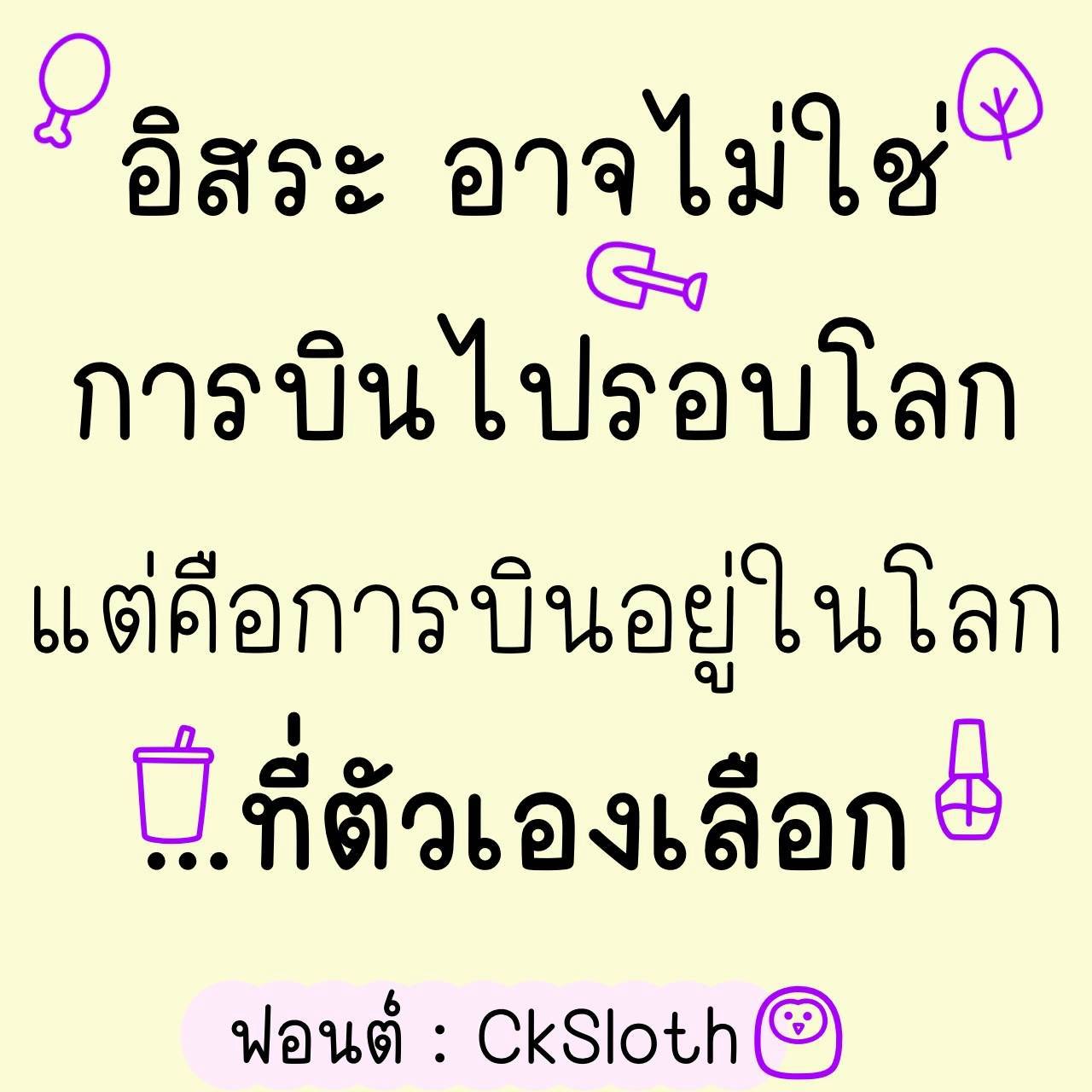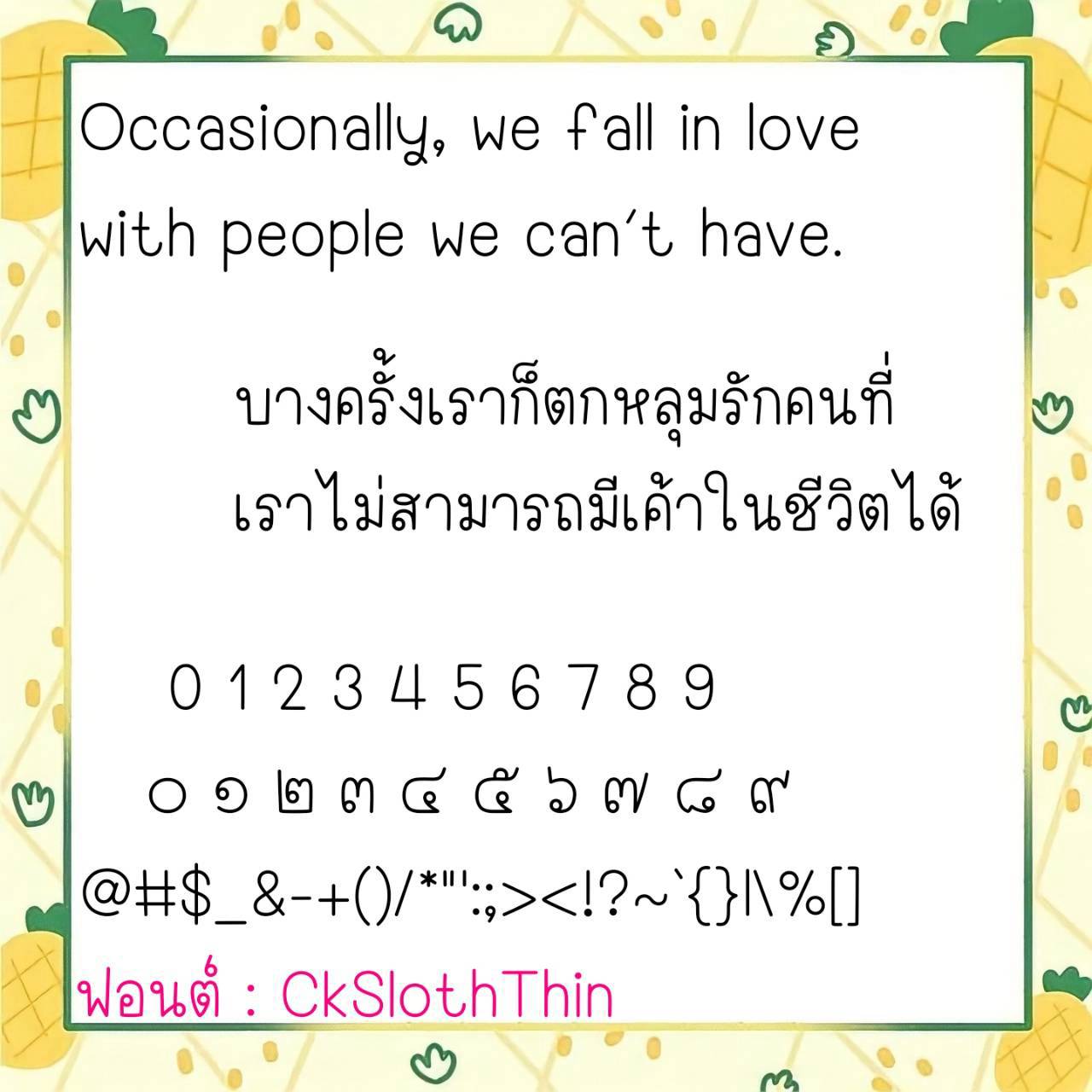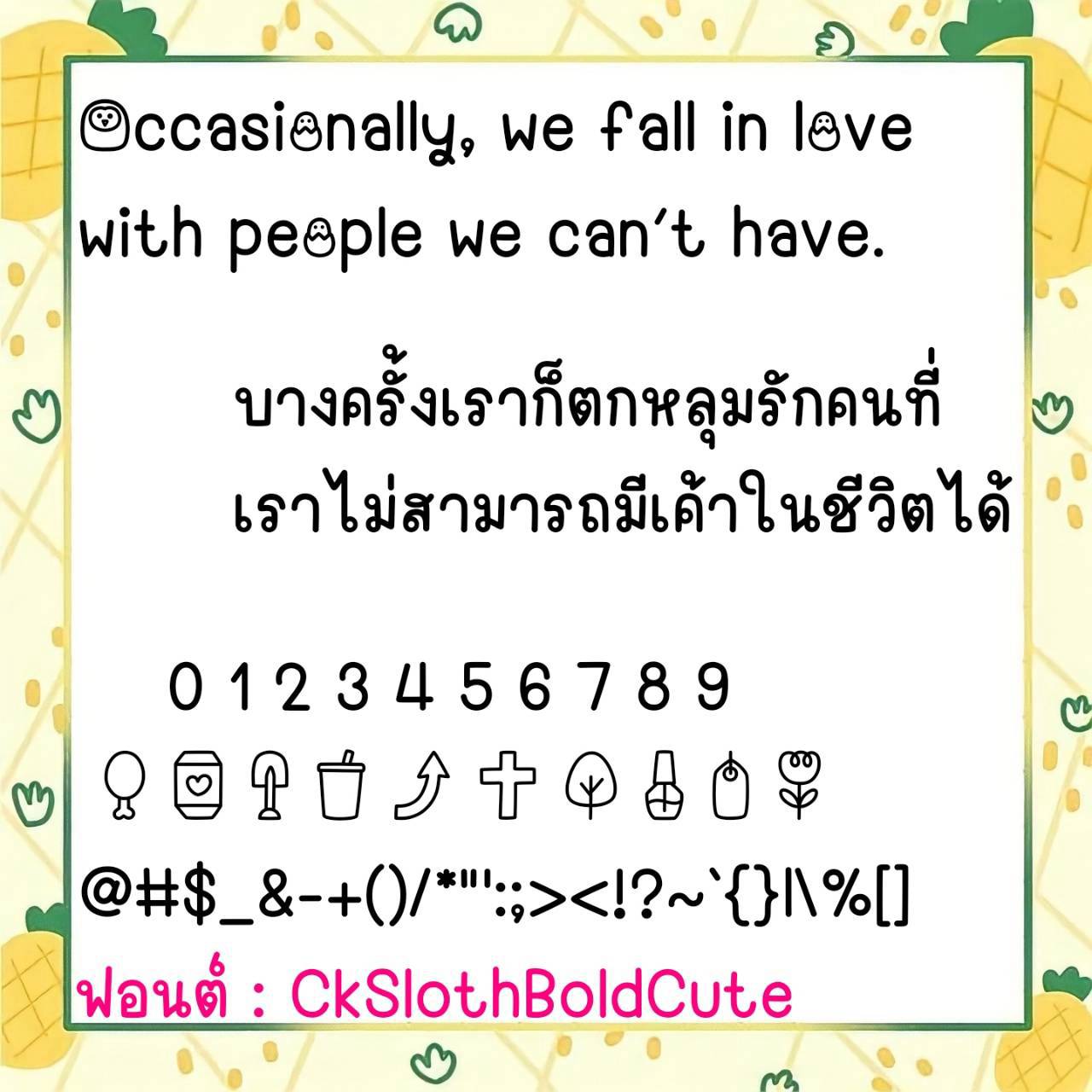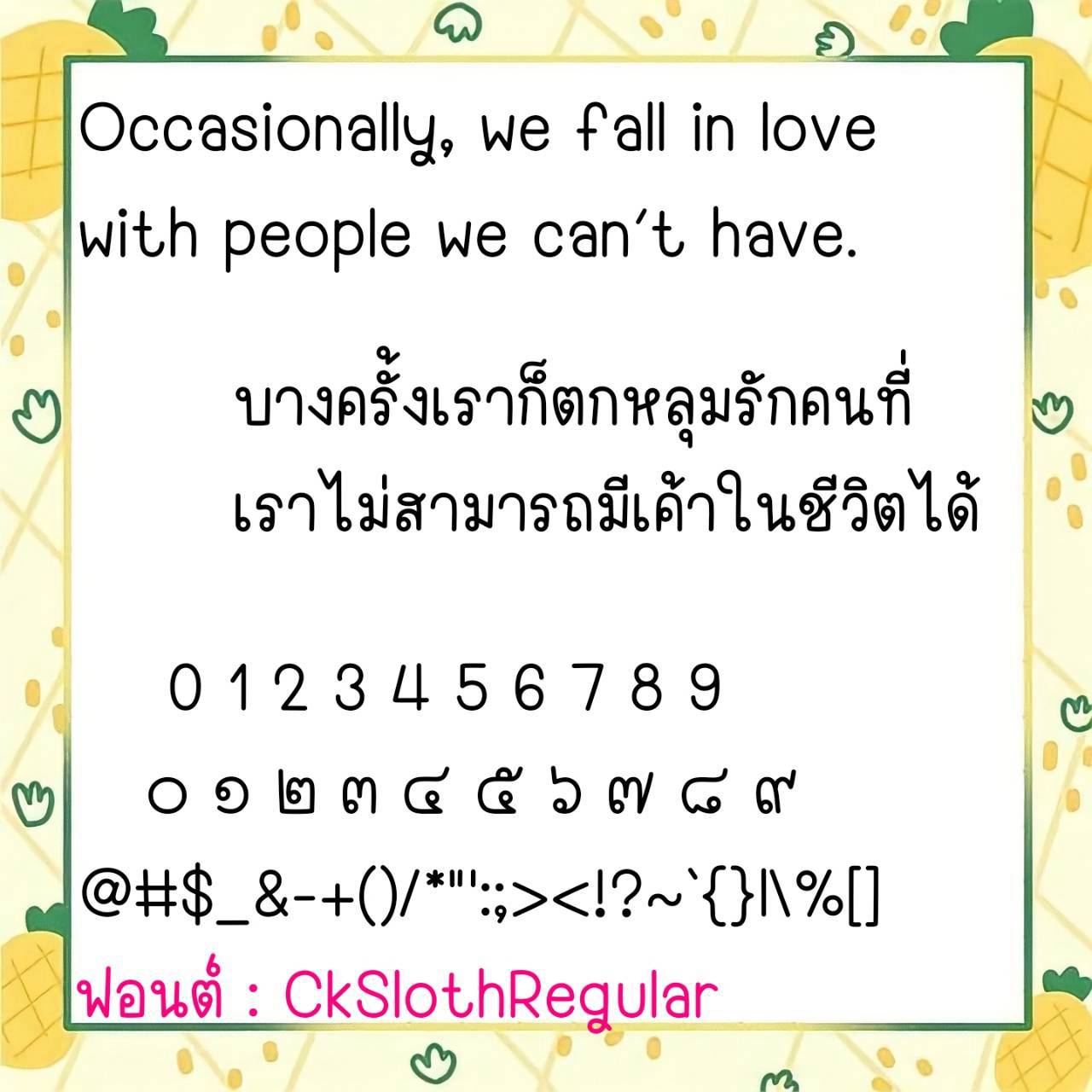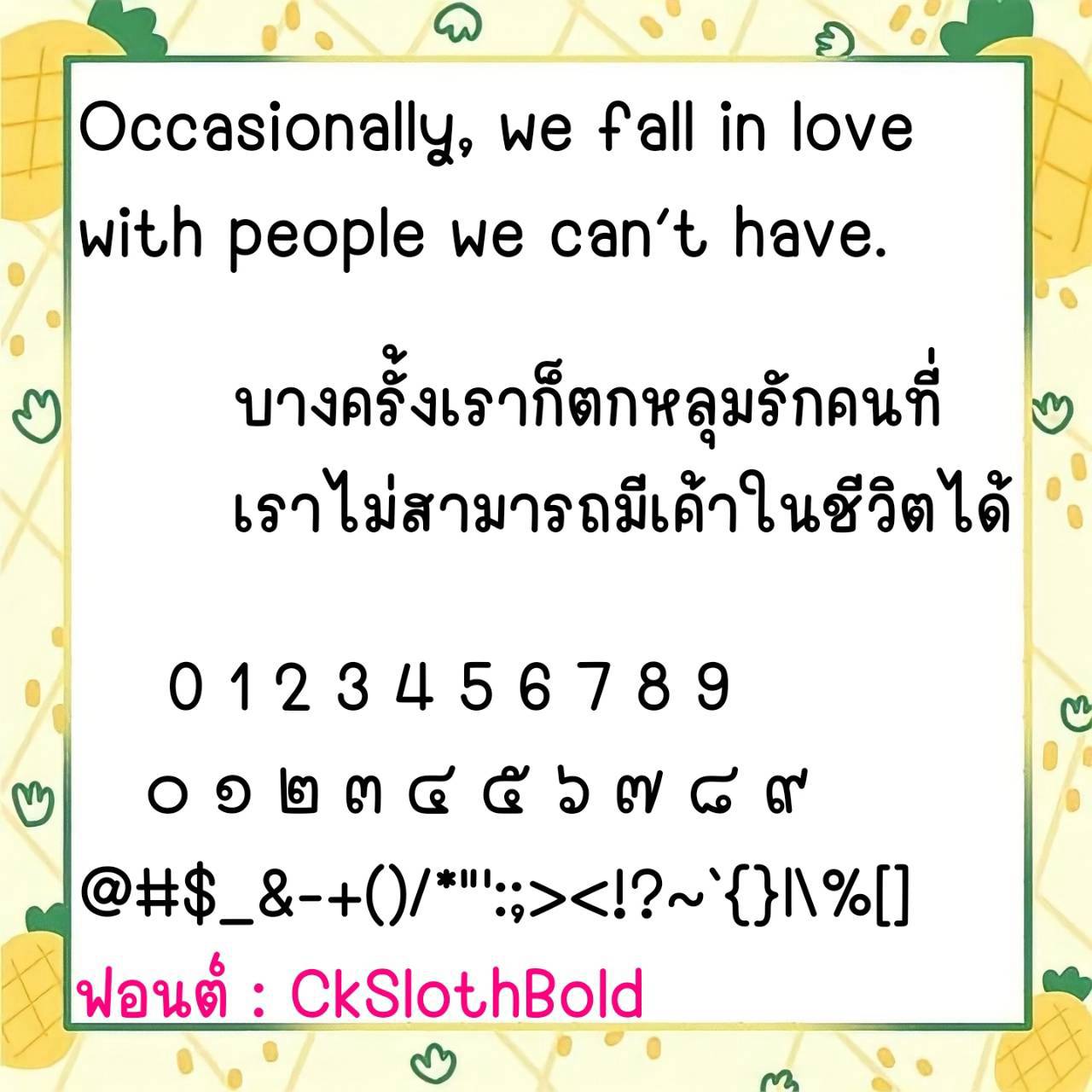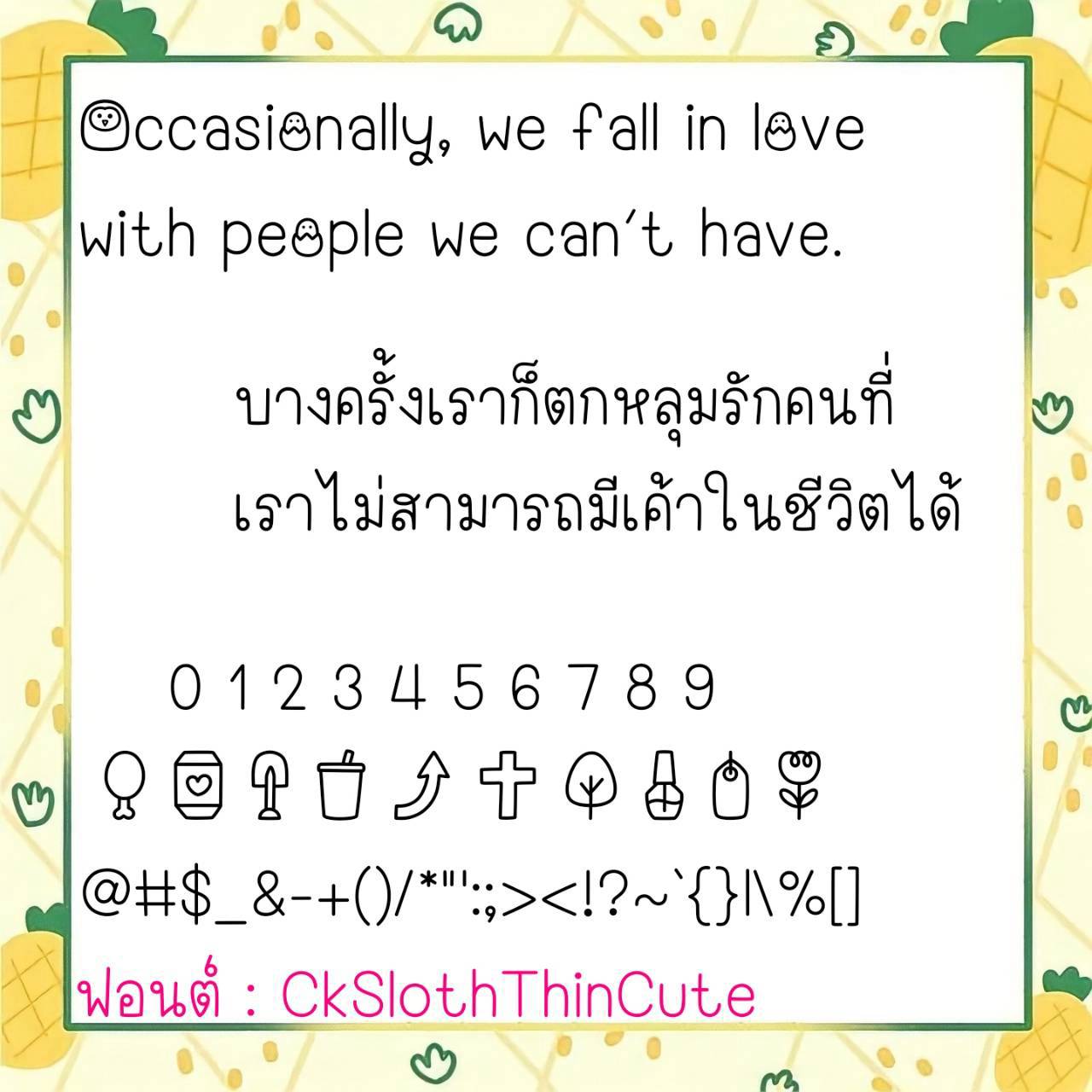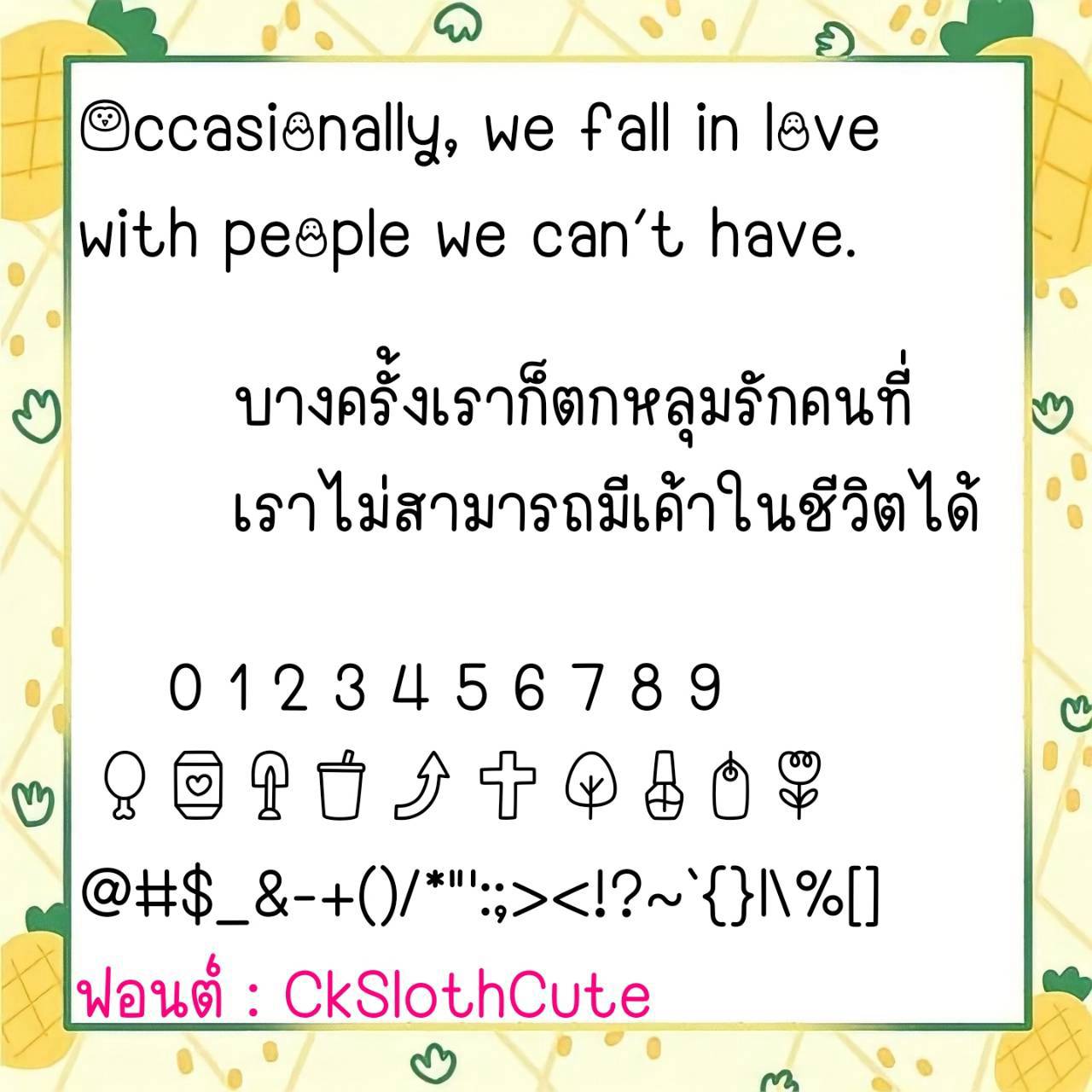
Font CkSloth
ชื่อสินค้า : Font CkSloth 💙
🔸 ฟอนต์ลายมือแนวน่ารัก สไตล์วัยรุ่น ขนาดตัวเล็กๆ ใช้งานได้หลากหลาย และยังมีไฟล์อิโมจิน่ารักๆที่ใช้แทนเลขไทยให้ด้วยค่ะ 🥰💙
🔹 A cute, handwritten font in a youthful style, small in size, versatile for various uses, and also includes cute emoji files that can be used to replace Thai numerals. 🥰💙
🔸ฟอนต์ลายมือแนววัยรุ่น มีความยึกยัก น่ารักมีสไตล์ดูมีลูกเล่น ดูไม่น่าเบื่อ และยังมีไฟล์อิโมจิน่ารักๆที่ใช้แทนเลขไทยให้ด้วยค่ะฟอนต์ปรับสระเรียบร้อยไม่ลอย ไม่เหลี่ยม ใช้งานได้กับทุกโปรแกรม ได้ทั้ง ios(รองรับกับแอพต่างๆที่รองรับฟอนต์ในios เช่น Goodnote, Procreate)/android/คอมฯ/Ps/Word,Excel ได้หมดจ้าาาาา❤️❤️❤️